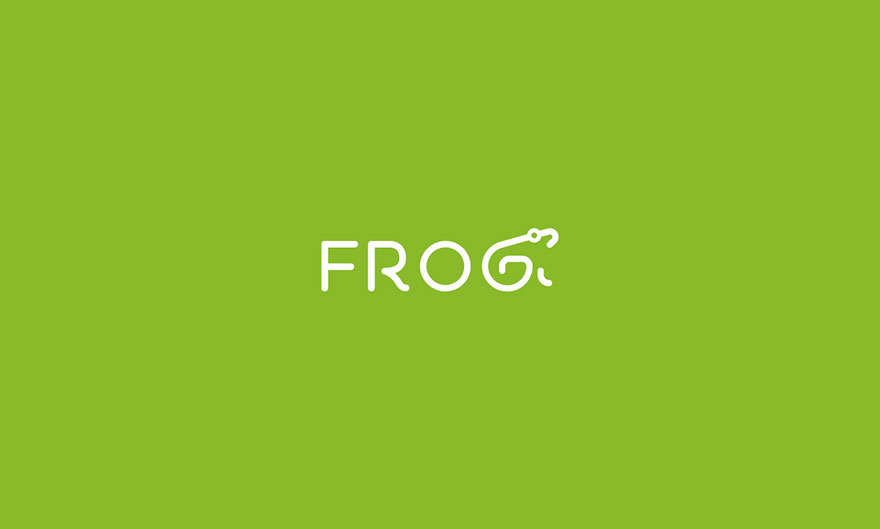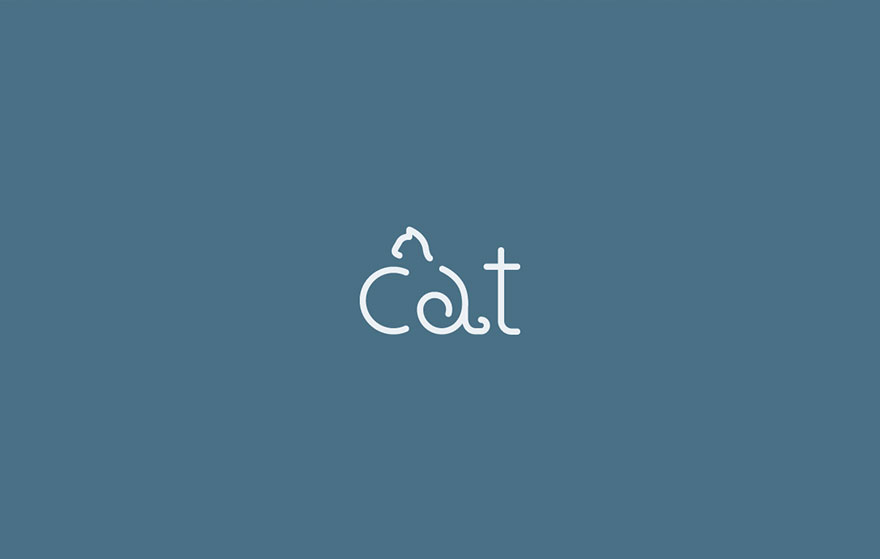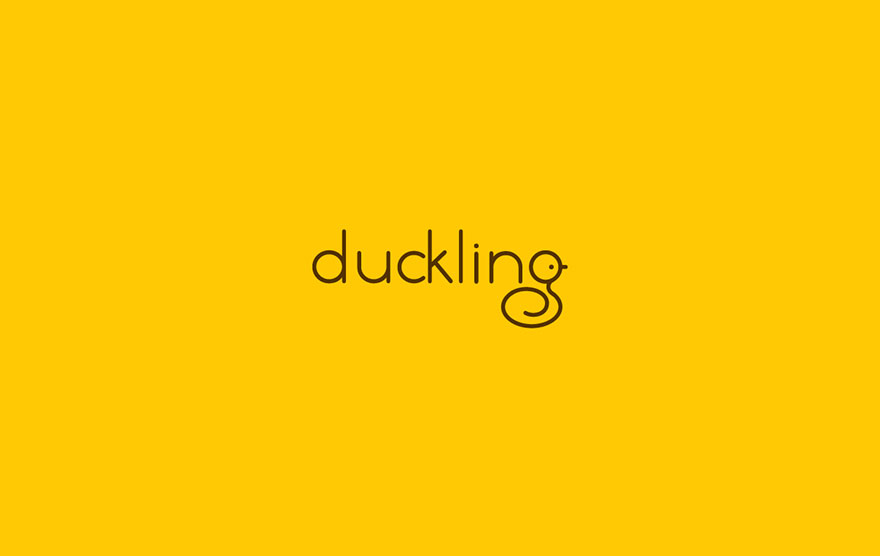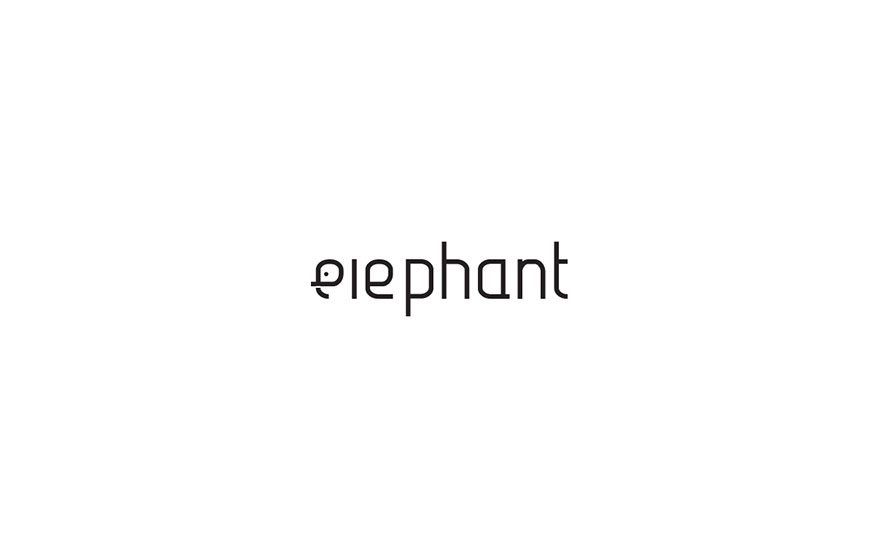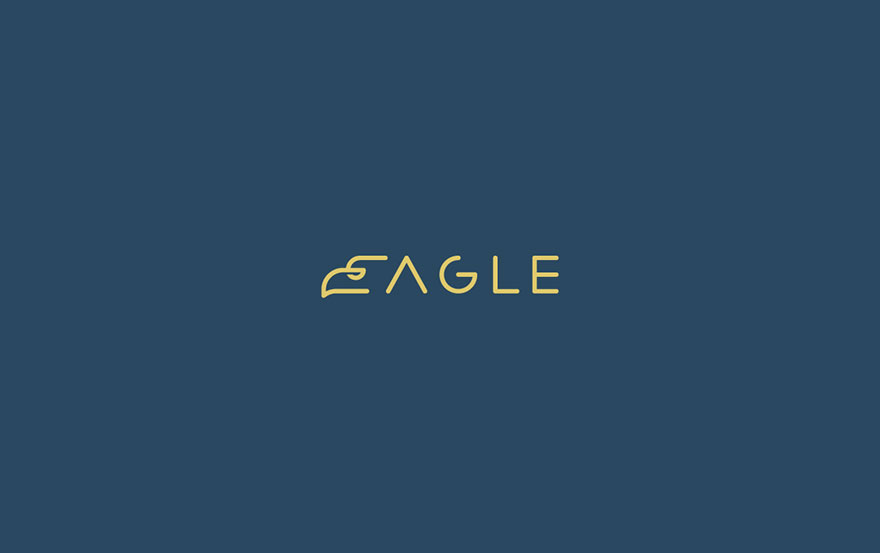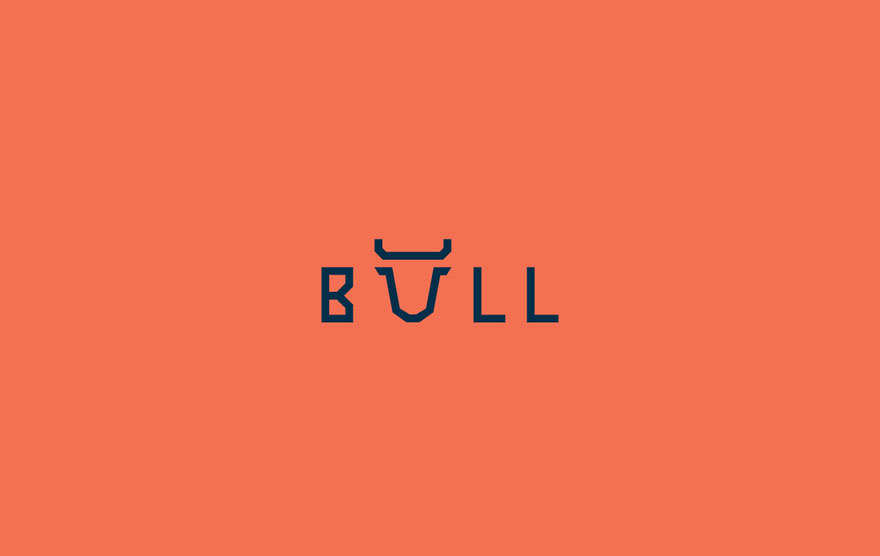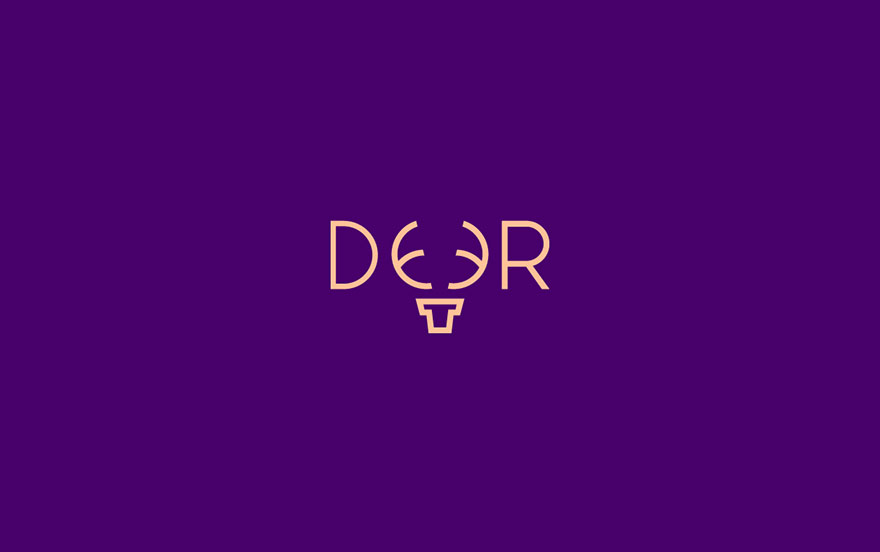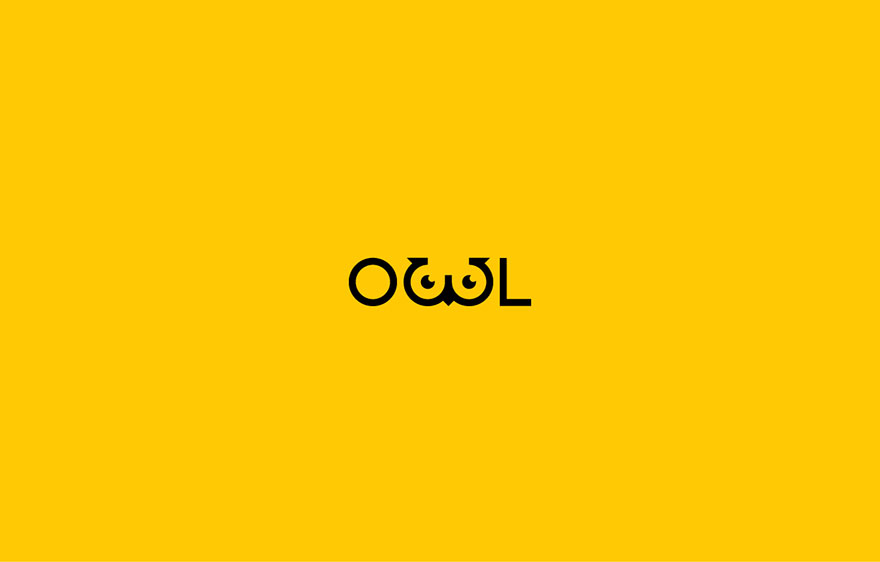
Designer cria tipografias minimalistas inspiradas em animais
Shibu PG é um designer gráfico talentosíssimo que criou recentemente uma tipografia super criativa e inspirada em animais.
Na série o designer modificou apenas algumas palavras para remeterem o animal citado, como na palavra “cat” a letra “a” se transforma em um gatinho, assim todos os nomes tem algo diferente para lembrar os animais, de uma forma criativa e sem alterar a fonte criada.
Tudo de uma forma bem minimalista, que transforma sua criação em algo único.